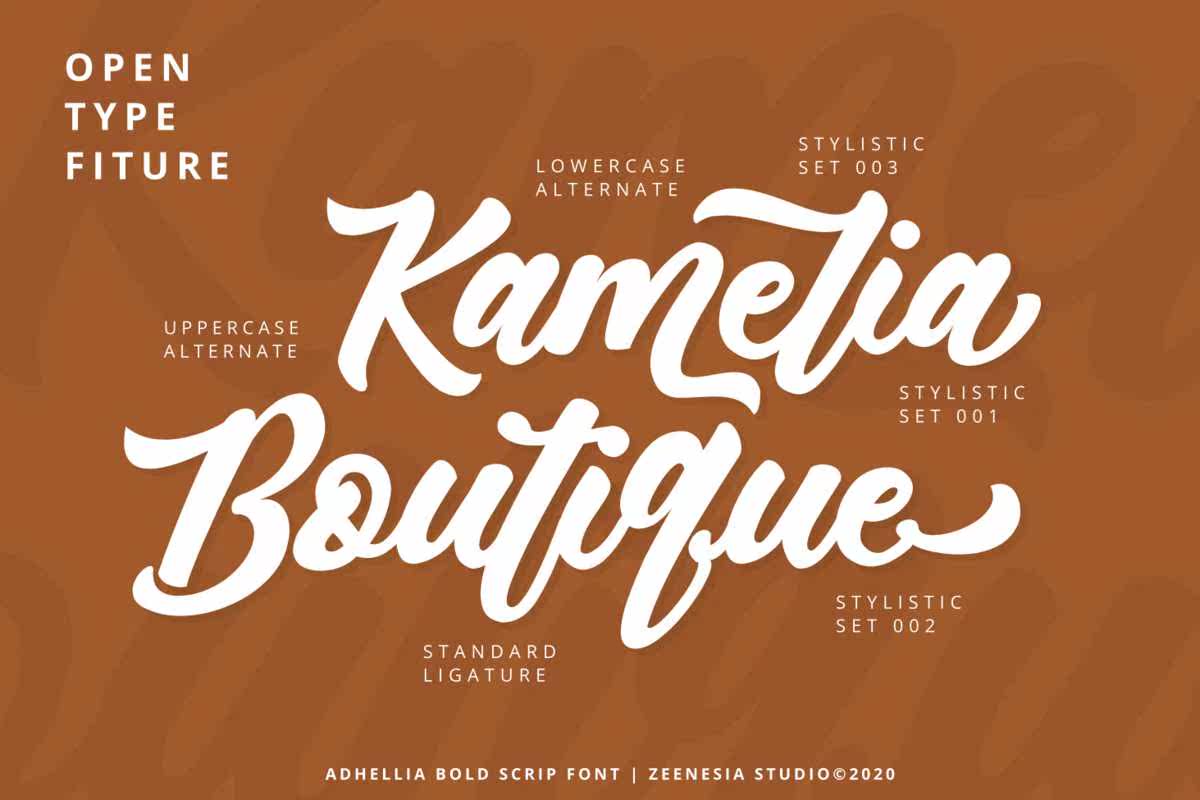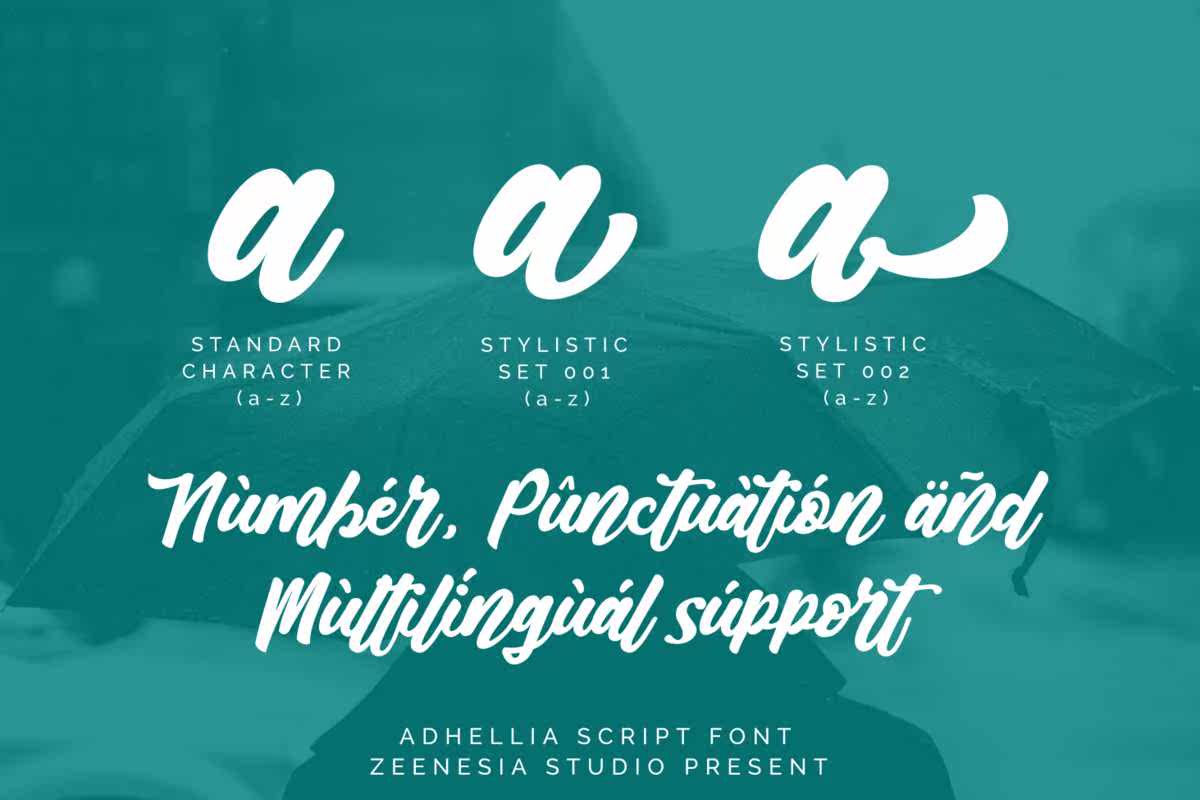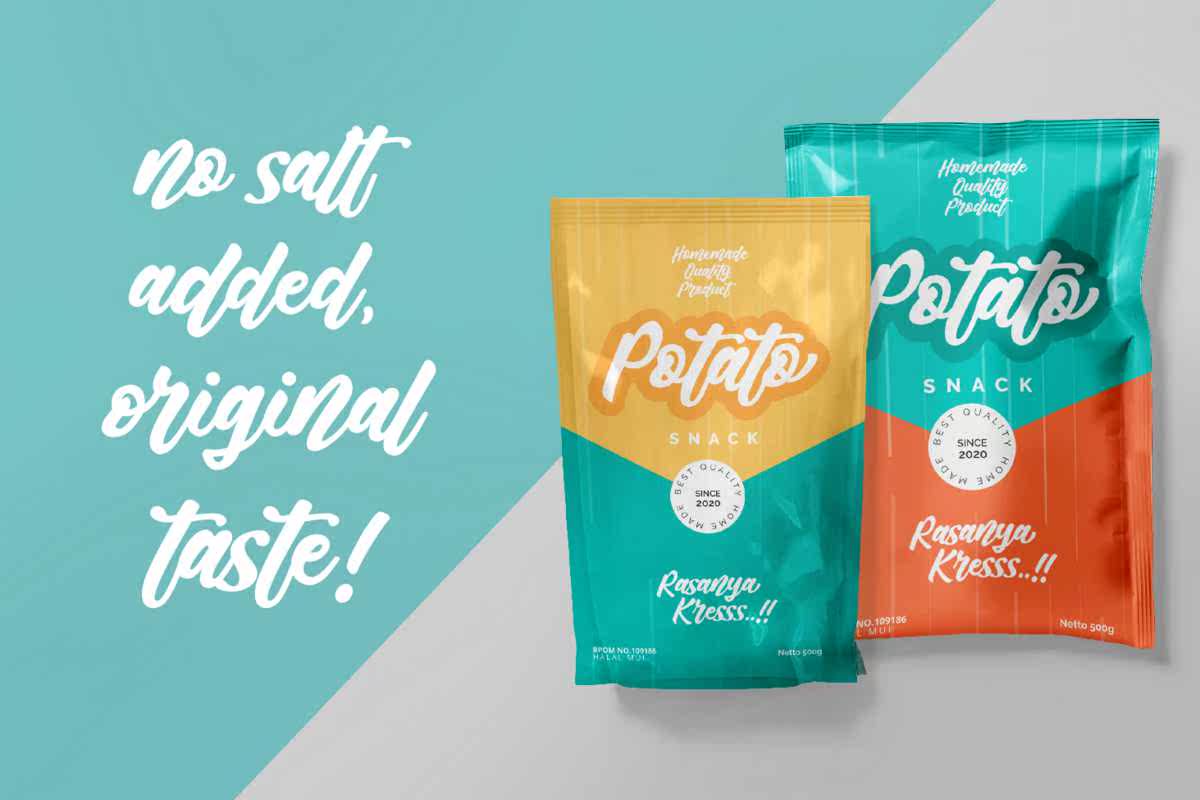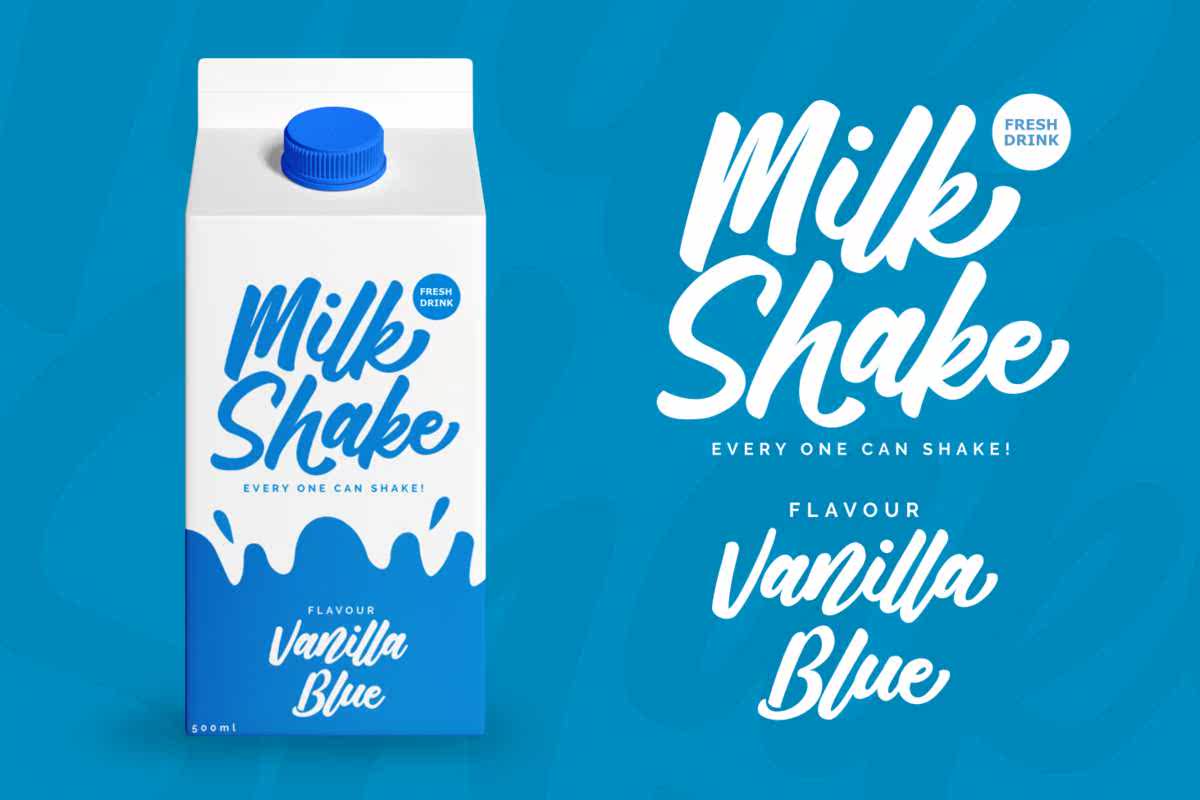
DHELLIASCRIPTISA和Lettered ScriptFont。它具有粗体和平滑的样式,并能完美地形成任何突出的设计。最适合于品牌、包装、印刷标题、T恤设计、食品设计和类似项目。DHELLIASCRIPTISA和Lettered ScriptFont。它具有粗体和平滑的样式,并能完美地形成任何突出的设计。最适合于品牌、包装、印刷标题,T恤设计、食品设计和类似项目。